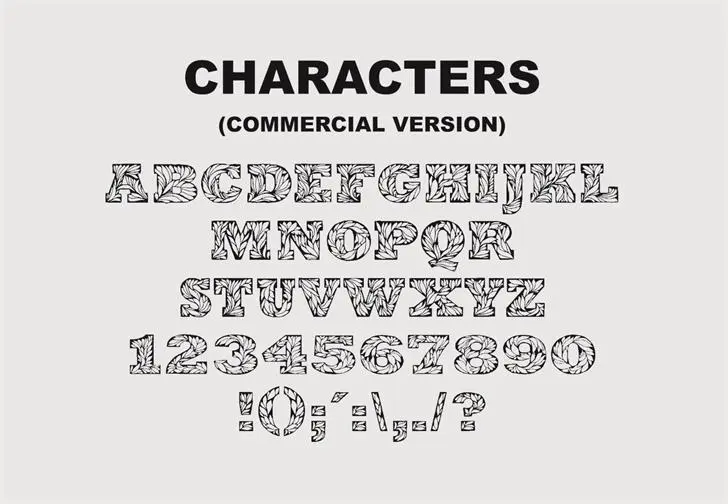
A fonte Leaffy Font é uma criação singular e única, ideal para designers buscando dar vida a seus projetos com um toque natural e envolvente. Com traços delicados e linhas suaves que imitam as folhas de árvores, esta fonte captura o espírito da natureza em cada caractere. Ela é perfeita para uso pessoal – seus designers podem se enriquecer com a versatilidade deste recurso gráfico único. Para ter acesso ao seu completo e comercial version, visite https://www.etsy.com/shop/DigitalTypefaceS. Esta fonte é mais do que simplesmente uma forma de escrever; ela é um elo visual entre criatividade e natureza.
Designer: Eva Barabasne Olasz